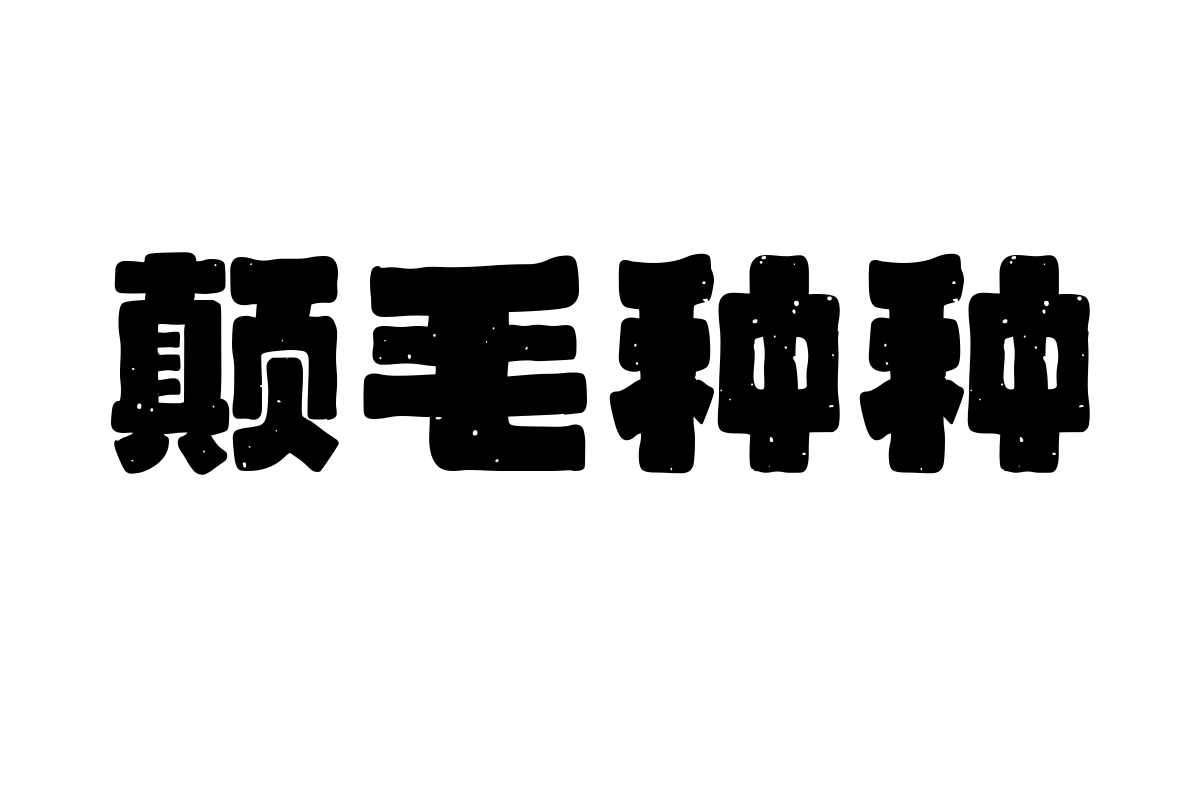
山海黄油曲奇w是一款字体,它的设计灵感来源于中国传统的山海经神话故事。这款字体具有独特的艺术风格和视觉效果,适合用于各种与中国传统文化相关的设计项目。
山海黄油曲奇w字体的特点如下:
1. 字形独特:山海黄油曲奇w字体采用了独特的笔画和结构,使得每一个字都显得生动有趣。这种独特的字形设计使得字体在视觉上具有较高的辨识度,能够吸引人们的注意力。
2. 艺术感强:山海黄油曲奇w字体具有很强的艺术感,无论是从线条的流畅性还是从整体的协调性来看,都展现出了很高的艺术水平。这使得这款字体非常适合用于需要强调艺术感的设计项目中。
3. 文化内涵丰富:山海黄油曲奇w字体的设计灵感来源于中国传统的山海经神话故事,因此它蕴含了丰富的文化内涵。这使得这款字体在传递信息的同时,还能够传达出一种独特的文化气息,让人印象深刻。
4. 适用范围广泛:山海黄油曲奇w字体适用于各种与中国传统文化相关的设计项目,如广告、海报、包装、网页等。这使得这款字体具有很高的实用价值,能够满足不同用户的需求。
总之,山海黄油曲奇w字体是一款具有独特艺术风格和视觉效果的字体,适合用于需要强调文化内涵的设计项目中。